MasterCard’s logo zonder woordmerk (is typografie dood?)
Als fonts konden spreken, wat zouden ze dan zeggen? Het is wellicht een vreemde vraag, maar we gebruiken fonts dag in dag uit voor onze communicatie. We kiezen ze bewust, vanuit een esthetisch maar ook vanuit een communicatiestandpunt.
Fonts hebben een krachtig, visueel effect op mensen. Ze kunnen luid, zacht, speels, serieus zijn en elk gewenst gevoel effectief overbrengen. Daarmee zijn ze een perfect transportmiddel voor emotie in communicatie. Sterker nog, ze visualiseren onze (gesproken) communicatie. Zonder typografie geen woorden. Zonder woorden geen communicatie. Maar is dat wel zo nu Mastercard een logo zonder woordmerk ontwikkeld heeft?
Waarom een blog over typografie
Fonts zijn belangrijker voor de communicatie dan je als communicatieprofessional wellicht denkt of je realiseert. Daar wil ik aandacht aan geven en ik wil het hebben over een interessante ontwikkeling in de markt.
Een logo zonder woordmerk. Kan dat wel?
Jullie hebben wellicht meegekregen dat Mastercard na 50+ jaar heeft beslist het woordmerk uit hun logo en op de meeste merkuitingen weg te laten. Ze vertrouwen volledig op de overlappende rode en gele bollen. Adieu ‘Mastercard’.
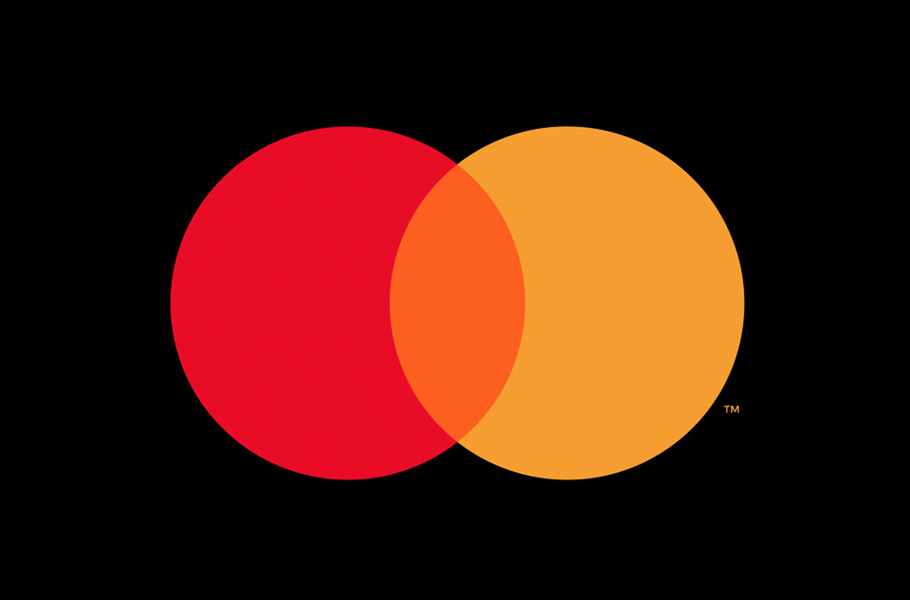
Deze ontwikkeling is niet nieuw. Een aantal grote merken is Mastercard voorgegaan. Denk aan Nike, Apple en McDonalds. Al deze merken hebben jarenlang door branding, marketing en communicatie naamsbekendheid bij hun doelgroep opgebouwd voordat ze overgestapt zijn op een logo zonder woordmerk. Apple herken je aan de appel. Nike herken je aan de swoosh. McDonalds heeft enorme zuilen aan de snelweg staan met hun M erop.
Toch zie je ook veel jonge(re) merken als Twitter, AirBnB en Facebook die glanzen door krachtige beeldmerken en een logo zonder woordmerk. Eenvoudige, herkenbare, krachtige logo’s die bedoeld zijn voor een mobile-first lifestyle.
Wat betekent dit voor communicatieprofessional
Ren nu niet direct naar je klant en adviseer hem niet meteen om zijn woordmerk weg te laten, omdat je een interessante trend hebt herkend. Dit is zeker niet voor iedereen geschikt en kan ook schade aanrichten aan een merk. Hoewel ‘typografische logo’s’ (logo’s zonder beeldmerk of icoon) gangbaarder worden, vereisen logo’s zonder woordmerk veel aandacht en strategie.
Hoe kun je als communicatieprofessional herkennen wanneer je klant klaar is voor de grote stap en wat doe je dan? Een aantal factoren is belangrijk;
- Onderzoek: Onderzoek de geschiedenis van het bedrijf en analyseer hoe sterk het merk in het bewustzijn van de doelgroep leeft. Hoe groot is het vertrouwen in de jarenlange relatie die je klant met zijn doelgroep opgebouwd heeft?
- Analyse: Analyseer of de markt de switch zou accepteren; is het een conservatieve of progressieve markt? Is het een merk dat hoofdzakelijk in het web communiceert, of ook in print?
- Communiceer: Maak het bespreekbaar; niet elke klant wil / snapt een dergelijke switch of ziet dit als de toekomst van zijn merk.
- Verander: Doe de transitie behoedzaam en stap voor stap; begin met digitaal, en volg dat op met print.
- Focus: Focus sterker op de merkbeleving door middel van de andere merkelementen (Brand Assets) zoals kleur, vorm, fotografie, iconografie, slogan, jingle, etc.
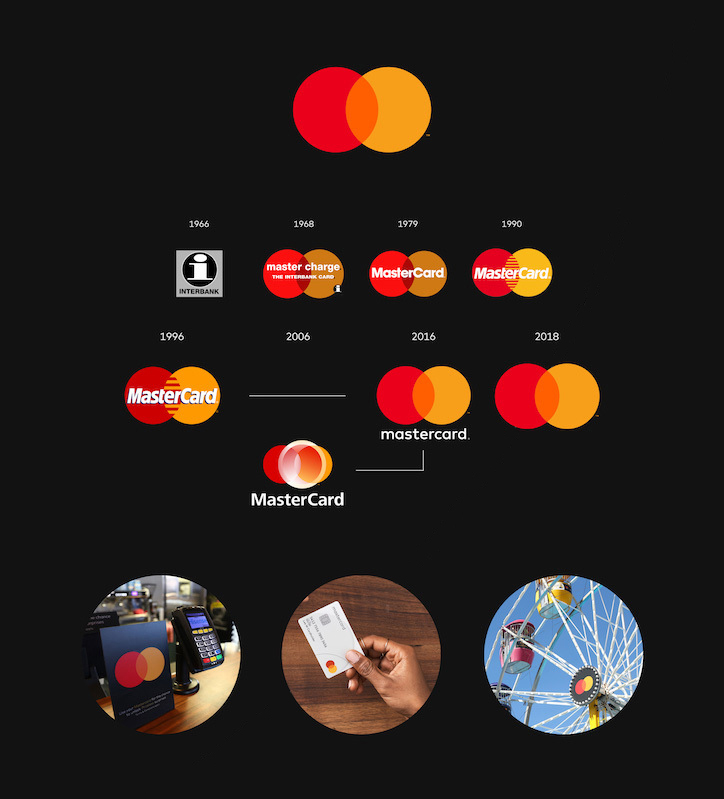
Is typografie dood?
Absoluut niet. Het is zelfs levendiger dan ooit! Teksten op het web en in print blijven bestaan, e-mails blijven je lastigvallen, etc. Het geschreven woord in communicatie leeft van typografie.
Een logo zonder woordmerk is zeker een mogelijkheid om je merk op een interessante manier in de markt te zetten, maar heeft het een serieus bestaansrecht?
Over de auteur
René Verkaart is (naast Stoere Binken Design) Type Director van Characters Font Foundry, een creatieve type foundry van eigen bodem. Zij creëren retail fonts & custom font design oplossingen voor merken wereldwijd. Ze zijn gespecialiseerd in handgemaakte branding-, verpakking- en advertising lettertypes. Hun fonts worden door designers en creatieve bureaus uit de hele wereld gebruikt voor branding-, editorial- en web / app projecten.